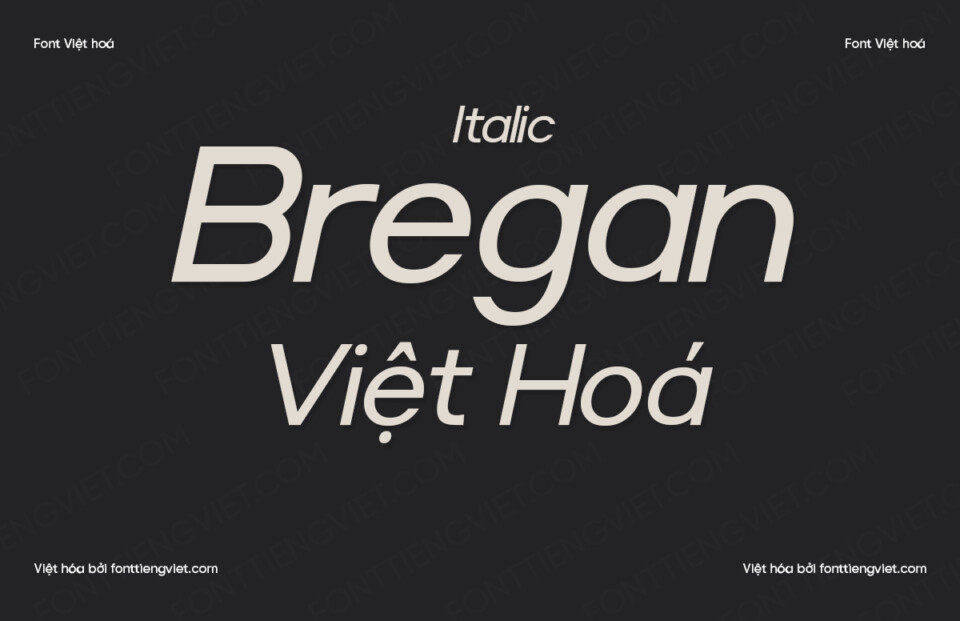
Font Việt hóa 1FTV VIP Bregan Italic
Giới thiệu về Font Việt hóa 1FTV VIP Bregan Italic
Trong thế giới sáng tạo đồ họa hiện nay, việc lựa chọn một bộ Font Miễn Phí chất lượng luôn là ưu tiên hàng đầu của các nhà thiết kế chuyên nghiệp lẫn các bạn học sinh sinh viên. Một trong những cái tên đang làm mưa làm gió trong cộng đồng font chữ chính là Font Việt hóa 1FTV VIP Bregan Italic. Đây là một bộ font mang phong cách hiện đại, thanh lịch nhưng không kém phần phá cách, giúp mọi sản phẩm thiết kế trở nên nổi bật và có sức hút riêng biệt đối với người xem ngay từ cái nhìn đầu tiên.
Đặc điểm nổi bật của Font Việt hóa 1FTV VIP Bregan Italic
Kiểu dáng nghiêng đầy nghệ thuật
Đúng như tên gọi của mình, Font Việt hóa 1FTV VIP Bregan Italic sở hữu những đường nét nghiêng (italic) vô cùng uyển chuyển. Sự kết hợp giữa độ dày vừa phải của thân chữ và những góc bo tròn tinh tế tạo nên một cảm giác chuyển động không ngừng. Điều này rất phù hợp cho các thiết kế cần tính năng động như banner quảng cáo thể thao, bìa tạp chí thời trang hay các tiêu đề video ngắn trên mạng xã hội. Sự cân bằng giữa tính thẩm mỹ và khả năng đọc giúp bộ font này chiếm trọn tình cảm của người dùng.
Khả năng hiển thị tiếng Việt hoàn hảo
Một trong những điểm yếu của nhiều bộ font nước ngoài chính là lỗi dấu khi gõ tiếng Việt. Tuy nhiên, với phiên bản Font Việt hóa 1FTV VIP Bregan Italic, mọi vấn đề về hiển thị đã được giải quyết triệt để. Từng dấu câu, từ dấu sắc, huyền đến các ký tự đặc biệt như “đ”, “ơ”, “ư” đều được điều chỉnh tỉ mỉ để hòa hợp với cấu trúc tổng thể của chữ cái gốc. Điều này giúp các bạn học sinh dễ dàng sử dụng để làm bài thuyết trình, làm báo tường hoặc trang trí tài liệu học tập một cách chuyên nghiệp nhất.
Ứng dụng thực tế của bộ font trong thiết kế
Bạn có thể sử dụng Font Việt hóa 1FTV VIP Bregan Italic cho rất nhiều mục đích khác nhau. Trong môi trường học đường, bộ font này là lựa chọn tuyệt vời để thiết kế bìa tiểu luận, làm thiệp mời sự kiện trường học hoặc tạo các slide bài giảng sinh động. Trong lĩnh vực thương mại, nó thường xuất hiện trên các bao bì sản phẩm cao cấp, logo thương hiệu hoặc các ấn phẩm truyền thông yêu cầu sự sang trọng. Nhờ tính linh hoạt cao, bạn có thể dễ dàng phối hợp nó với các font chữ không chân khác để tạo nên sự tương phản thú vị và chiều sâu cho tác phẩm.
Kết luận về Font Việt hóa 1FTV VIP Bregan Italic